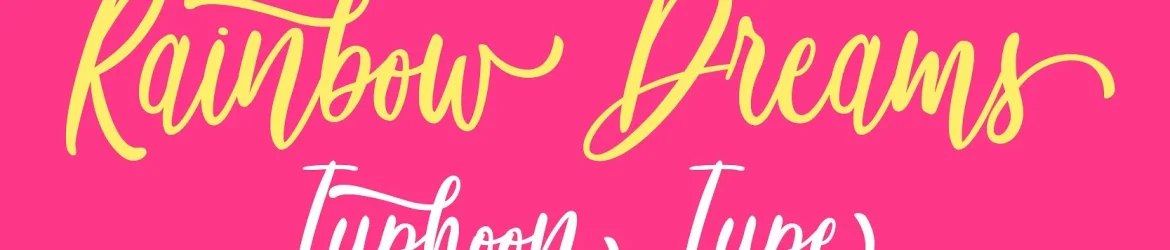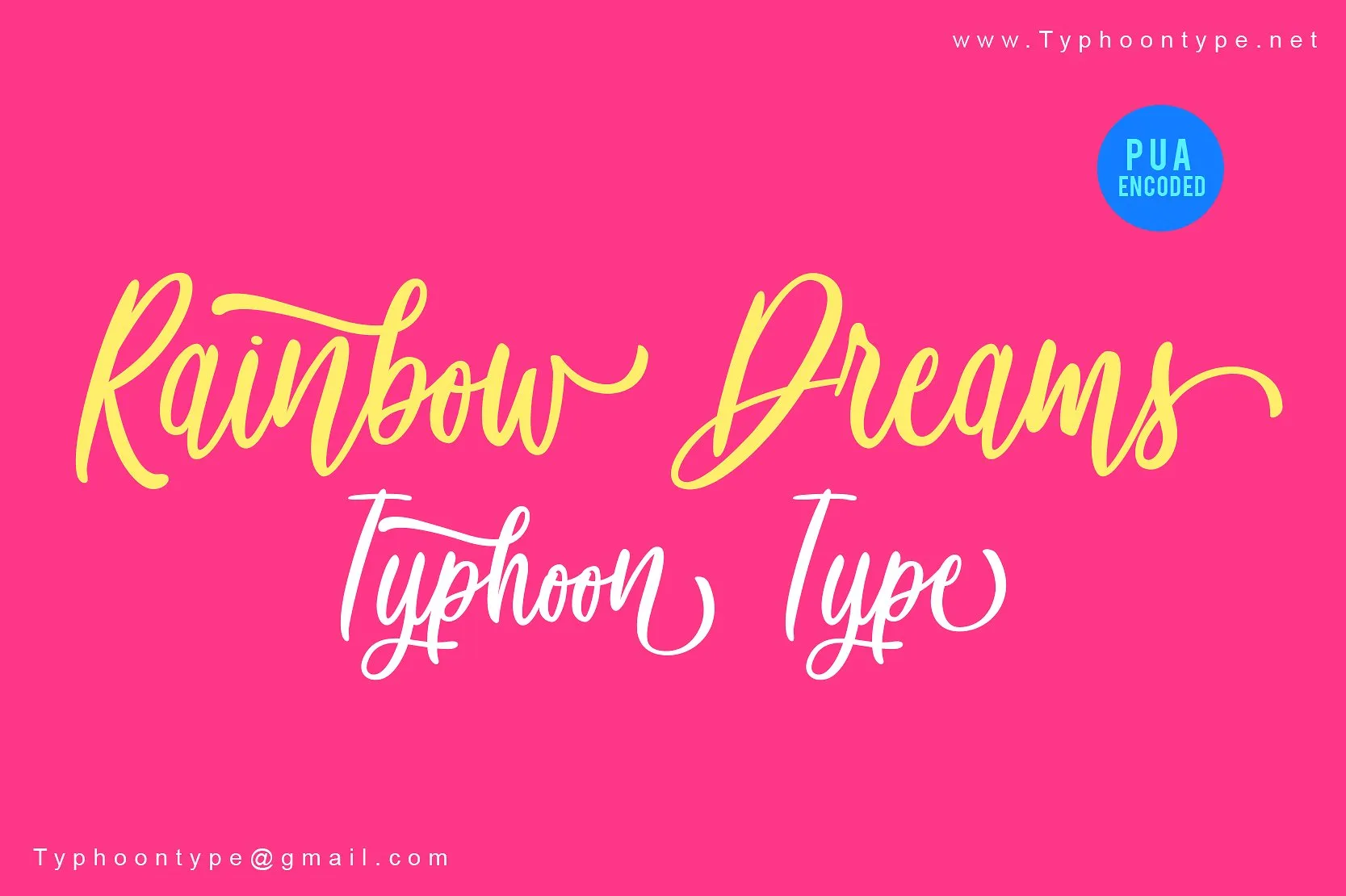
Rainbow Dreams Script Font
Aqui está uma descrição para a página de download da fonte ‘Rainbow Dreams Script Font’, seguindo as instruções fornecidas: Agradecemos por visitar nosso catálogo de fontes! Nós apresentamos Rainbow Dreams Font, um script casual e natural, ideal tanto para o dia-a-dia quanto para projetos mais específicos. Desenvolvido pelo designer zziplex, este tipo de texto é perfeito para criações casuais como convites para festas ou blogs, além de permitir a personalização de logotipos, capas de livros e até mesmo frases em suas estantes domésticas. Com sua elegante tipografia organicamente escrita, Rainbow Dreams Script Font se adapta perfeitamente tanto à identidade de negócios pequenos quanto às publicações mais formais. Seja para capas de livros, embalagens de produtos ou até mesmo anúncios em revistas e jornais – a seriedade do seu projeto será garantida graças aos detalhes delicados deste tipo de fonte. Por fim, Rainbow Dreams Script Font não apenas oferece um toque único ao seu trabalho, mas também uma maneira criativa de expressar suas ideias. Para aqueles que buscam algo mais despojado e personalizado para seus projetos digitais ou impressos, esta fonte certamente é a escolha perfeita. Já imaginou como ficariam seus anúncios ou capas de livro com essa font? Vamos te convidar para experimentar Rainbow Dreams Script Font e ver o impacto que ela pode ter em seu trabalho.